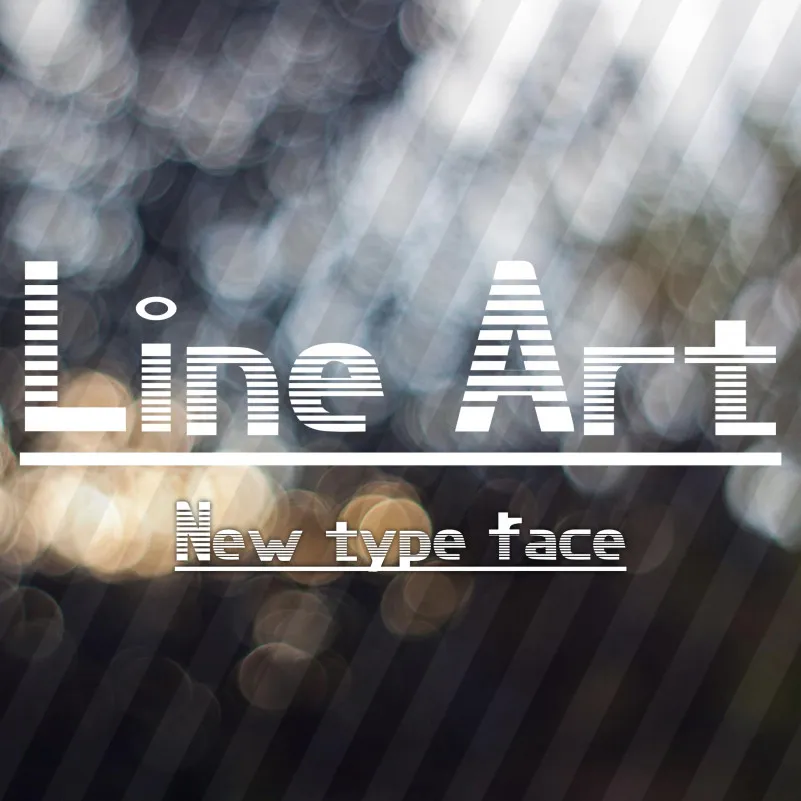
Line Art Display Font – Download Grátis
A Fonte Line Art Display é uma escolha perfeita para qualquer projeto que busque a simplicidade e modernidade do tipo sans serif. Seu design minimalista e geométrico, criado pelo designer chasim, destaca-se pela sua capacidade de se adaptar a diversos estilos de design. Ideal tanto para textos grandes quanto para elementos gráficos menores, essa fonte apresenta linhas rígidas e curvas simples que não cansam o olho enquanto mantêm uma sensação clara e contemporânea. Perfeita para criar designs que combinem elegância com praticidade, a Line Art Display oferece um toque de sofisticação ao mesmo tempo em que permanece acessível e versátil para qualquer necessidade visual. Instale-a agora para agregar sofisticação a seus projetos sem comprometer sua eficácia comunicativa.
Designer: chasim